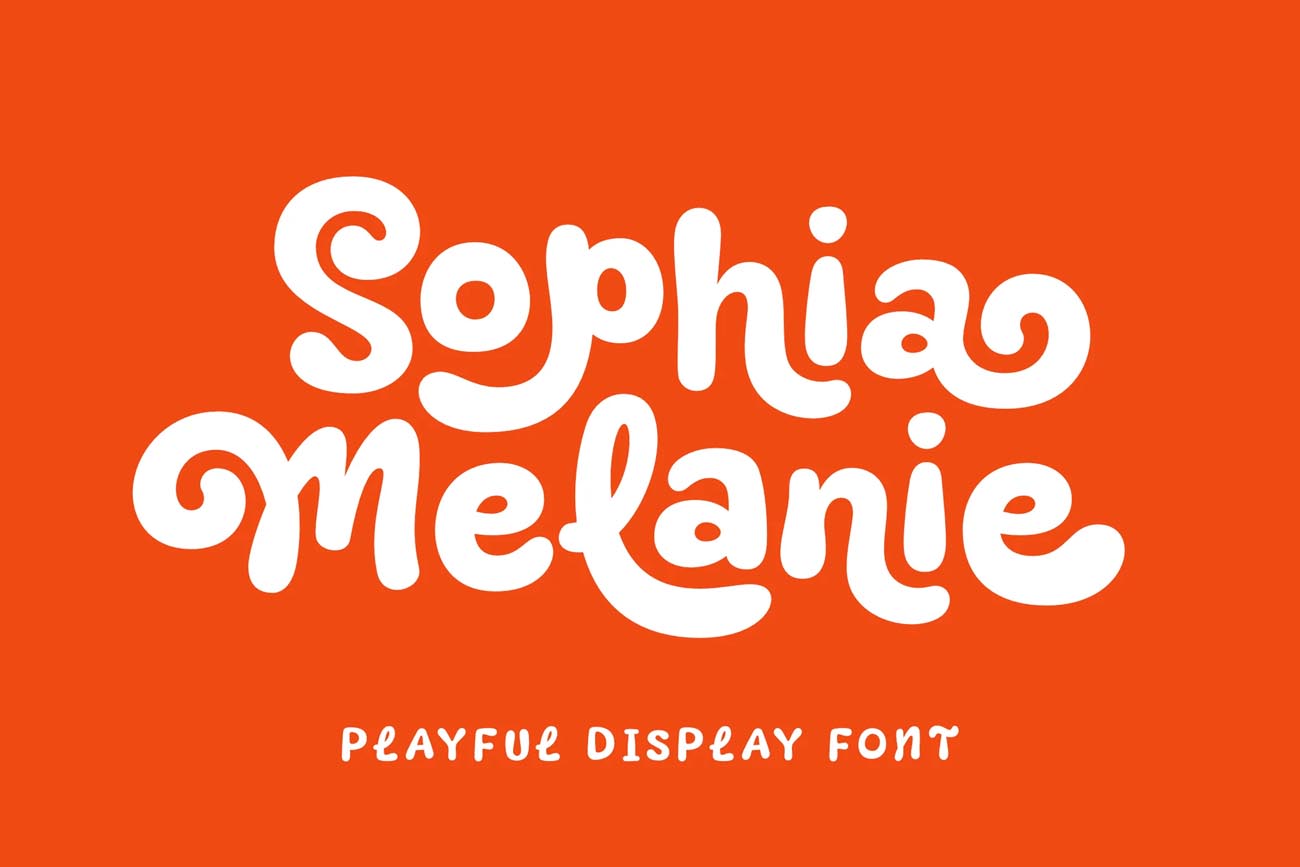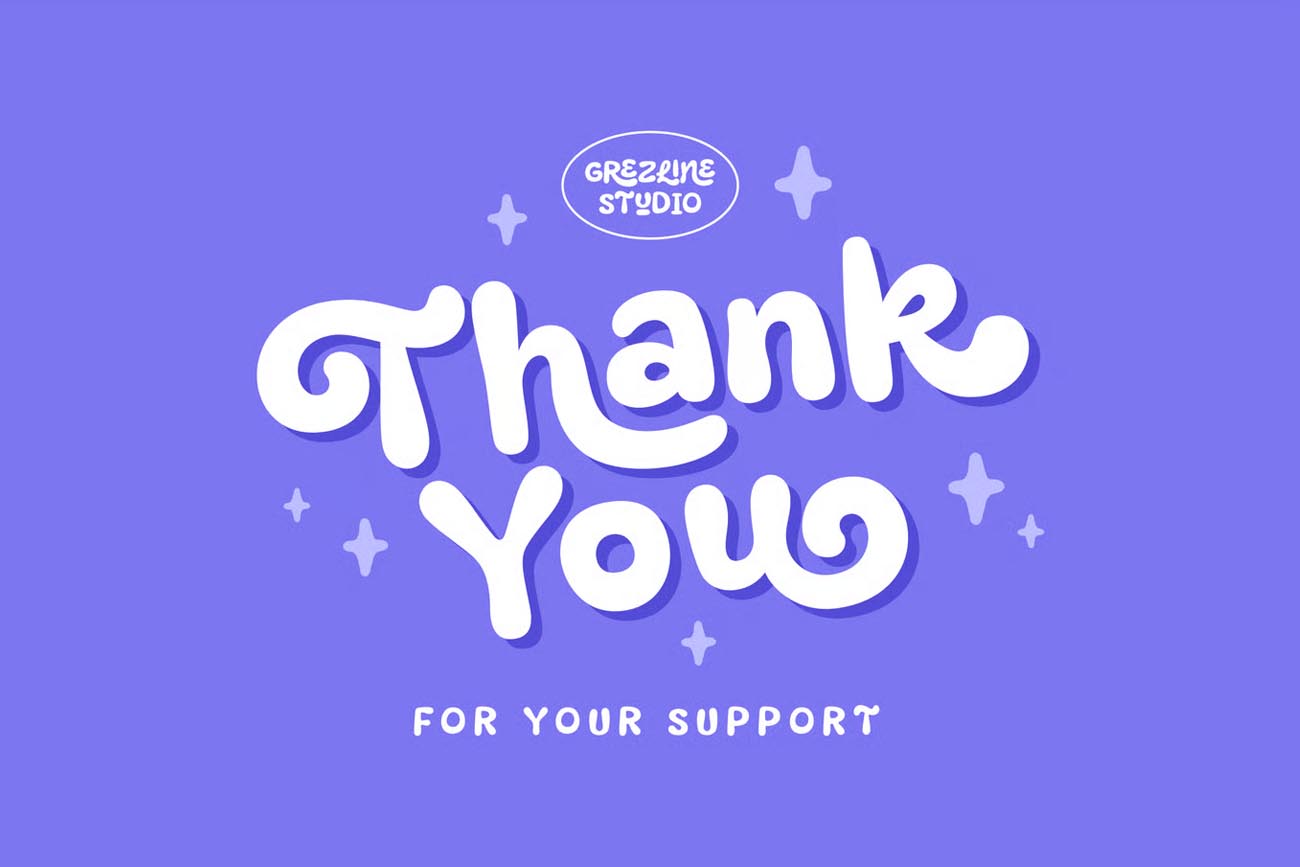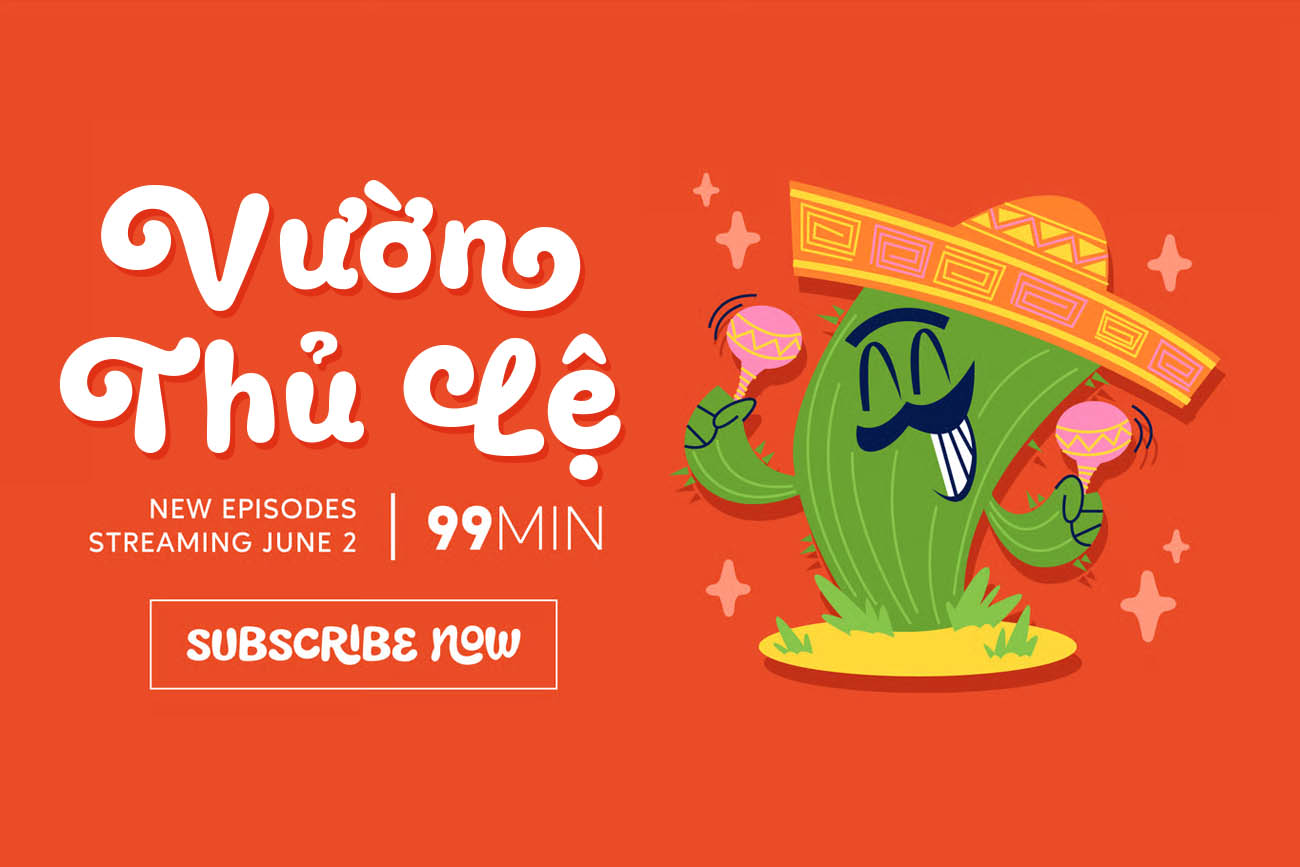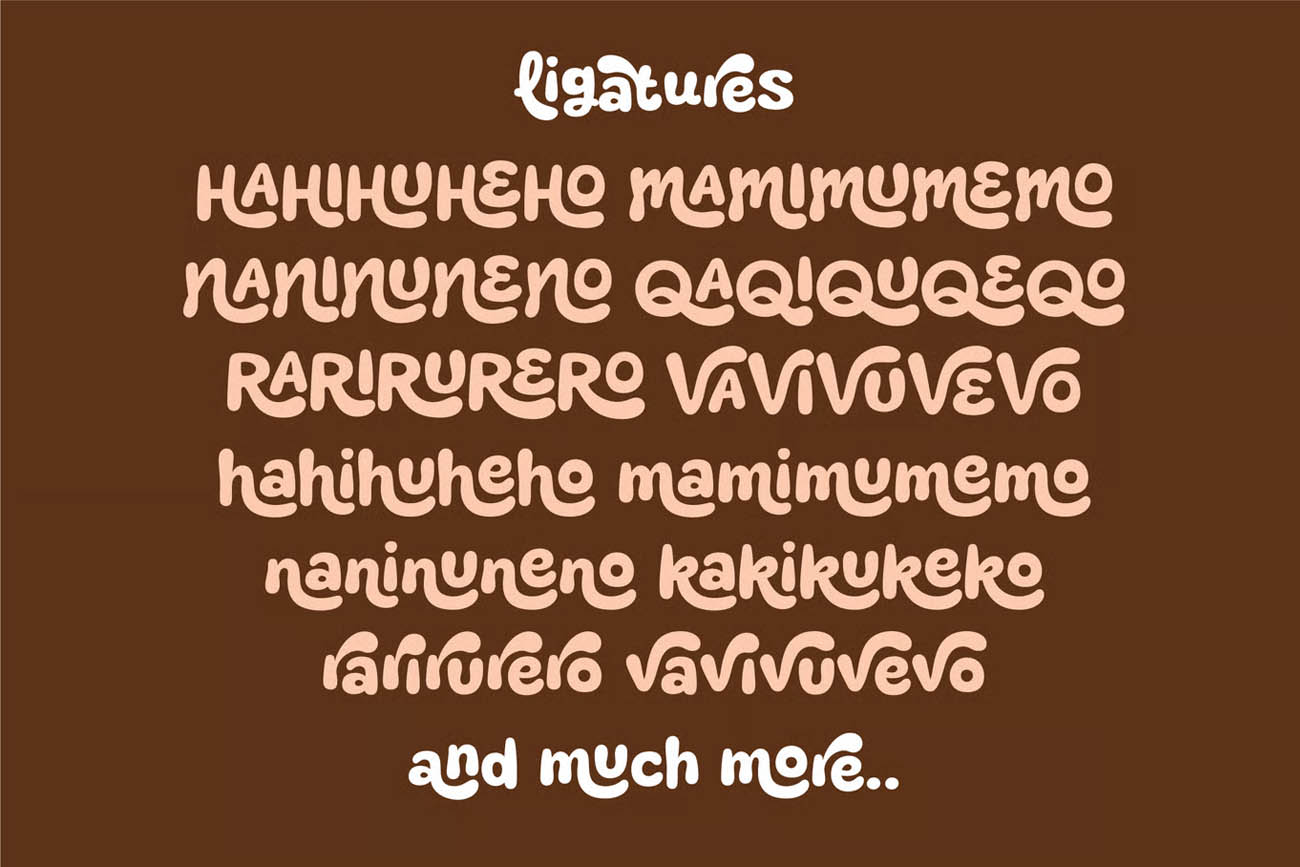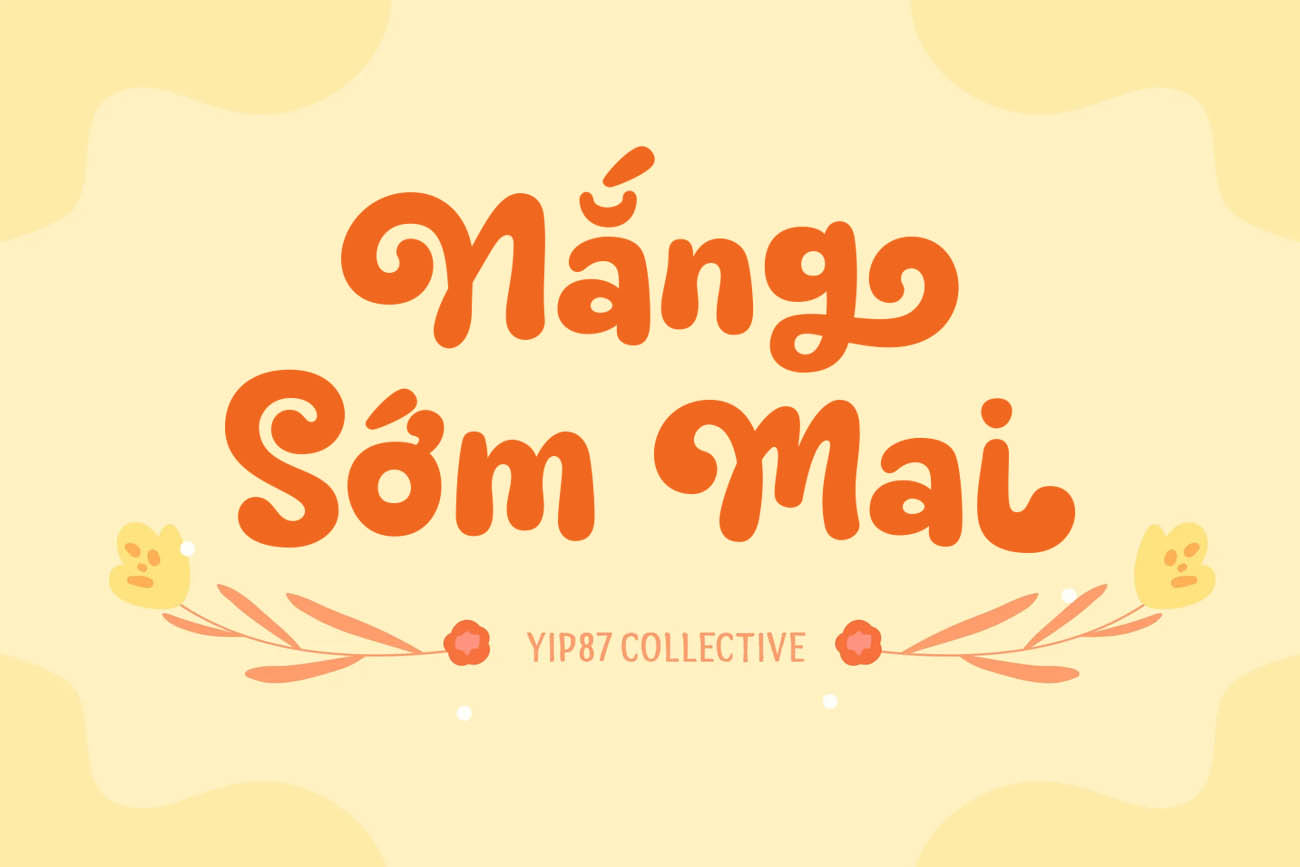
[Tải Về] Font Chữ TH Sophia Melanie Việt Hóa – Dễ Thương, Tròn Trịa
Tác giả Grezline
Bạn đang tìm một font chữ đáng yêu, tròn trịa và tràn đầy năng lượng cho thiết kế hướng đến trẻ em, tiệm bánh hay các sản phẩm sáng tạo? Font chữ TH Sophia Melanie Việt hóa chính là lựa chọn lý tưởng dành cho bạn.
TH Sophia Melanie là một font chữ display mang phong cách vui tươi, tròn trịa và mềm mại như bong bóng. Từng ký tự được thiết kế uốn lượn một cách nghệ thuật, tạo nên hiệu ứng thị giác sinh động và cực kỳ bắt mắt. Với các đầu nét được bo tròn, đậm nét, font tạo nên cảm giác dễ gần, đáng yêu và không kém phần chuyên nghiệp.
Font đặc biệt phù hợp cho:
• Thiết kế bao bì sản phẩm cho trẻ em, bánh kẹo, đồ chơi
• Logo tiệm bánh, cửa hàng quà tặng, thương hiệu thời trang trẻ
• Poster, tiêu đề sách thiếu nhi, đồ họa mạng xã hội
• Ấn phẩm cần sự vui nhộn và thân thiện với người dùng
Bộ ký tự phong phú, hỗ trợ ligatures độc đáo
Không chỉ có kiểu dáng bắt mắt, TH Sophia Melanie còn được trang bị:
• Bộ chữ cái in hoa và in thường đồng bộ, rõ ràng
• Số học, ký tự đặc biệt và dấu câu đầy đủ
• Hệ thống ligatures thông minh: các cặp chữ cái như “ha, hi, ho, mu, me, ke, ku…” được tự động kết hợp một cách liền mạch, tạo thành những tổ hợp chữ mềm mại và đẹp mắt.
Font TH Sophia Melanie Việt hóa là lựa chọn hoàn hảo nếu bạn đang tìm kiếm một phong cách vui nhộn, dễ thương và nổi bật cho các thiết kế hướng đến trẻ em hoặc sản phẩm thân thiện. Với đường nét uốn lượn đặc trưng, bộ ligature phong phú và hỗ trợ tiếng Việt đầy đủ – đây là font chữ xứng đáng có mặt trong thư viện của mọi nhà thiết kế sáng tạo.